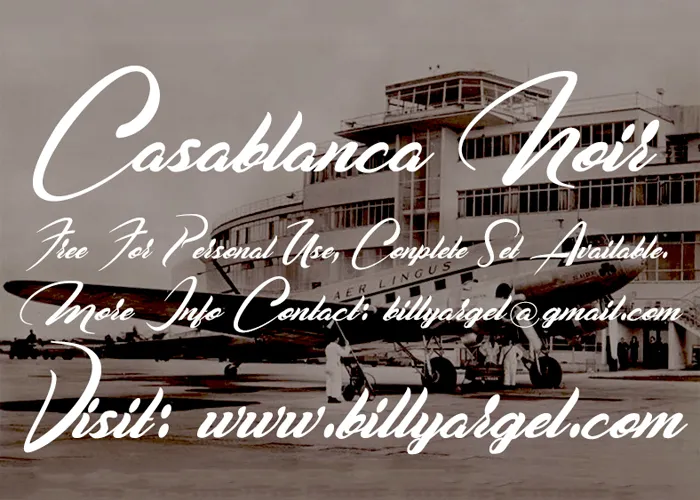
Casablanca Noir Font – Download Grátis
A Casablanca Noir é uma fonte escrita a mão criada pelo designer Hamilton. Esta elegante fonte tem um tom suave e sofisticado que se destaca perfeitamente para trabalhos pessoais, desde cartões de aniversário até relatórios pessoais. Em termos de usabilidade, ela oferece um toque autêntico que combina com estilos de escrita manuscrita tradicionais. A fonte é ideal para quem deseja adicionar uma nota única e elegante a qualquer projeto digital ou impresso. Ela também se destaca em títulos e subtítulos, proporcionando um acabamento gráfico incrível sem precisar de muito esforço adicional. Se você está procurando por uma fonte escrita a mão para seu próximo projeto pessoal ou comercial, a Casablanca Noir é definitivamente o tipo de recurso que você precisa em sua estante. Para quem deseja usar esta fonte para um projeto com fins comerciais, há completa disponibilidade da fonte e licenças. Para mais informações sobre o uso desta fonte e outras opções disponíveis, visite www.billyargel.com ou entre em contato por .